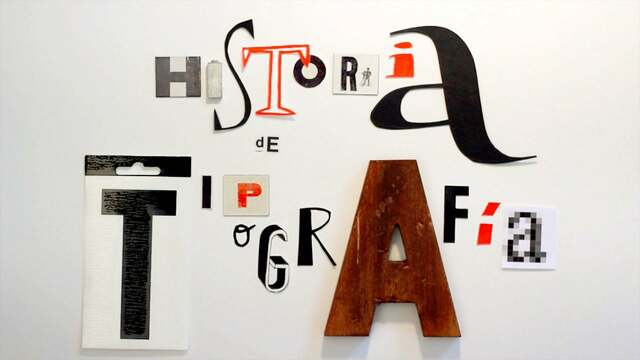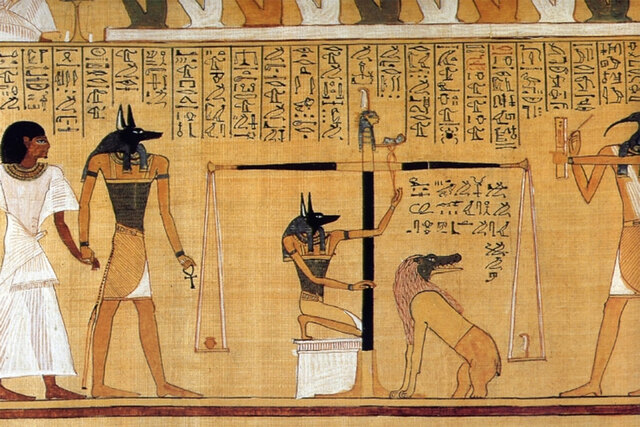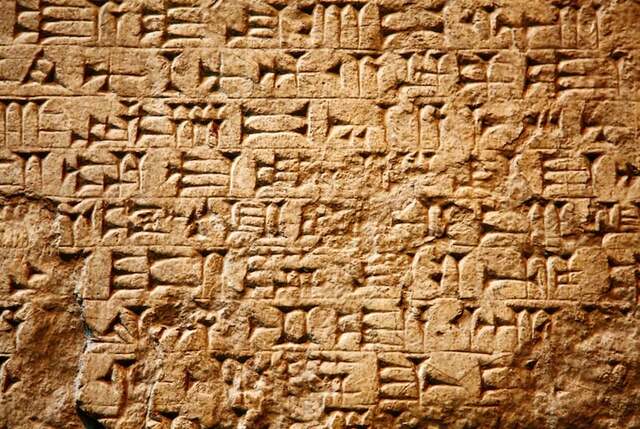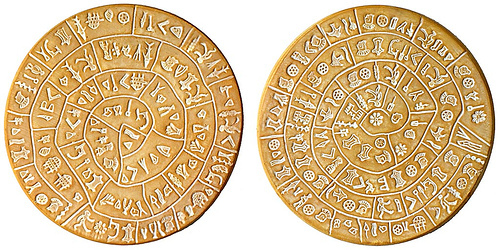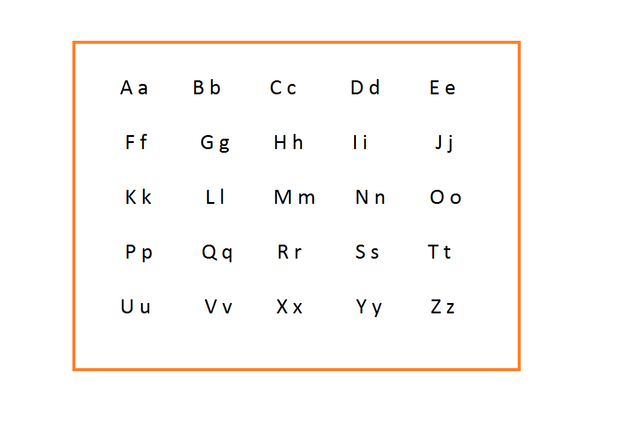
La civilización de los Sumerios realizaron aportes importantes como la escritura, en la cual se utilizaban pictogramas los cuales eran representaciones de objetos animados e inanimados.
Estas civilizaciones utilizaban los jeroglíficos como escritura, la cual se basaba en el uso de signos y representaciones.
Esta se solía graficar en muros o en un tipo de papel. -
Era un medio por el cual se representaban palabras por medio de pictogramas, los cuales eran aun mas abstractos que los jeroglificos.
Eran sistemas construidos y tallados con pictogramas los cuales estaban compuestos por figuras de partes del cuerpo, así como con algunos símbolos geométricos.
Estos tenían una estructura que estaba construida por un silabario de un centenar de caracteres, mas sin embargo los fenicios desarrollaron una nueva escritura con veintidós silabarios.
Los antiguos griegos tomaron el alfabeto fenicio y lo convirtieron 5 consonantes en vocales, además aplicaron una estructura geométrica a los desiguales caracteres fenicios.
En los monasterios un especialista muy culto que sabia griego y Latín, trabajaba como escritor y director de las escrituras.
Con ayuda del Copisti que era quien escribía las letras adornadas visualmente. (Generalmente eran libros religiosos-) -
Este ocurrio luego de que el alfabeto llego hasta los romanos, despues de que Spurius Carvilius diseñara la letra g para remplazarla por la z Griega. El alfabeto latino tenia 24 letras y se añadieron las: s,t,v y x.
Es esta época fue que hubo un ambiente factible para la tipografía, la demanda de libros era enorme.
A la Xilosofia ,se le denomina como aquella técnica para designar una impresión sobre una superficie. -
Johann Gensfleich zum Gutenberg desarrollo un complejo sistemas de pequeños bloques con letras del abecedario, los cuales al ser cubiertos con tinta y aceite eran presionados contra la superficie deseada logrando que se quedara plasmada la letra.
Esta provoco un camino en el papel social y económico de la comunicación tipográfica; Haciendo consigo un tipo de letra mas grueso y obscuro, que resaltara de los antiguos, añadiendo en el mismo nuevas letras en el abecedario como lo es la actual "Ñ".
Konrad Zuse fue el primero en construir una computadora que funcionase. Lo hizo en el salón de la casa de sus padres en Berlín. Este ordenador podía guardar 64 palabras.